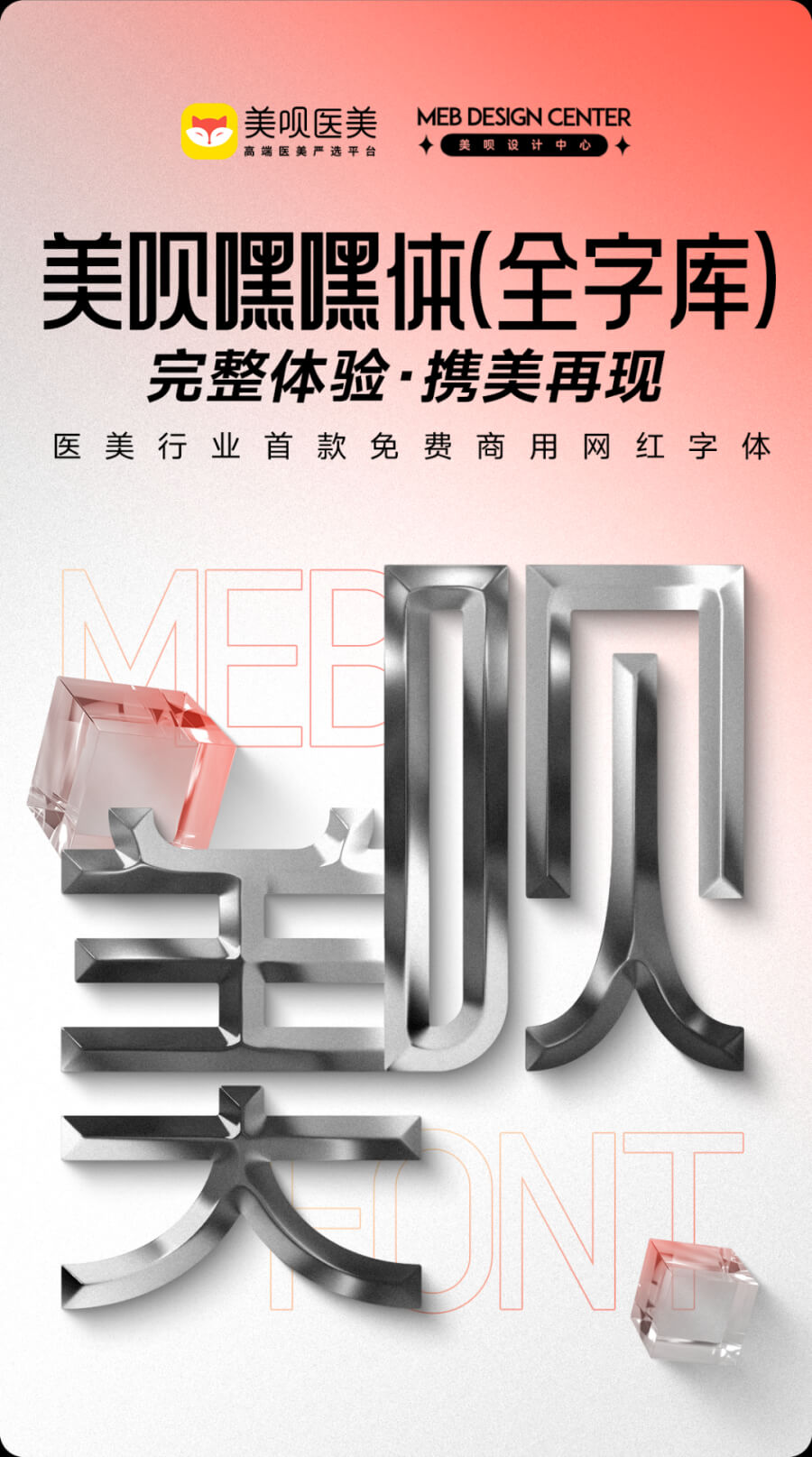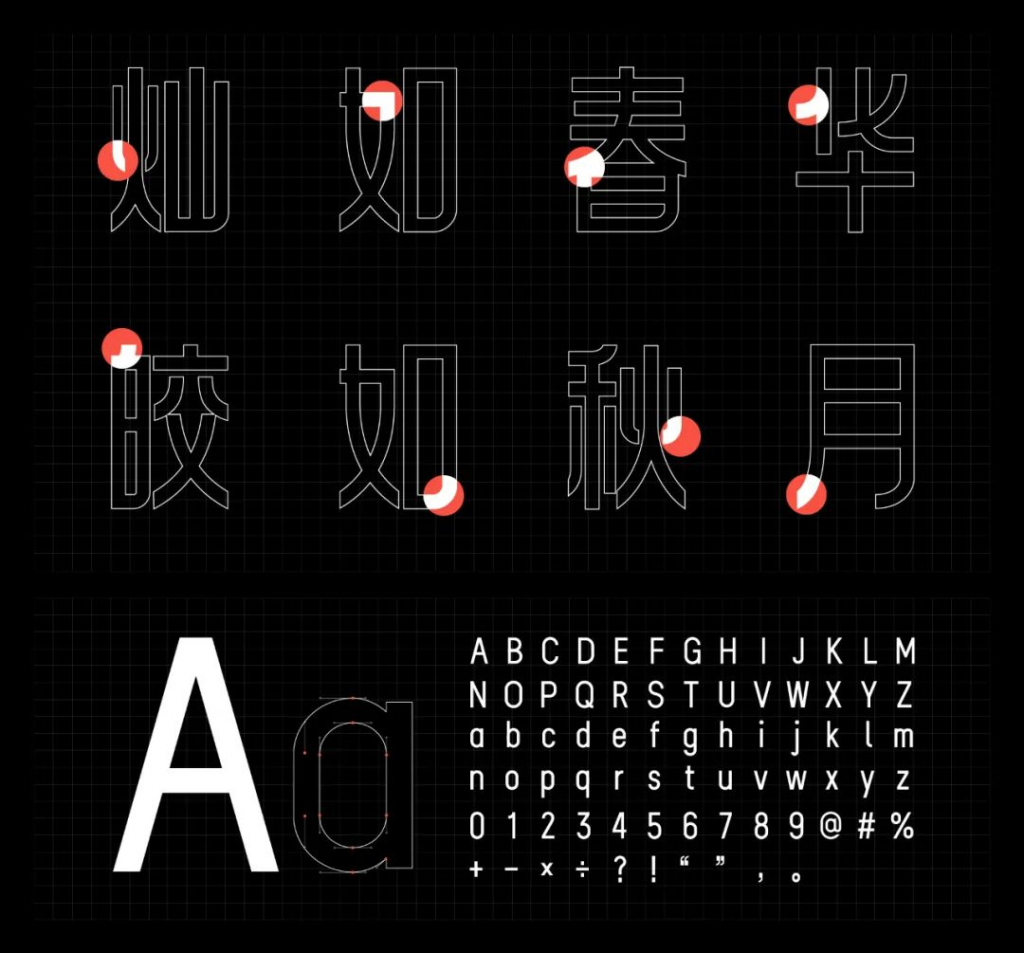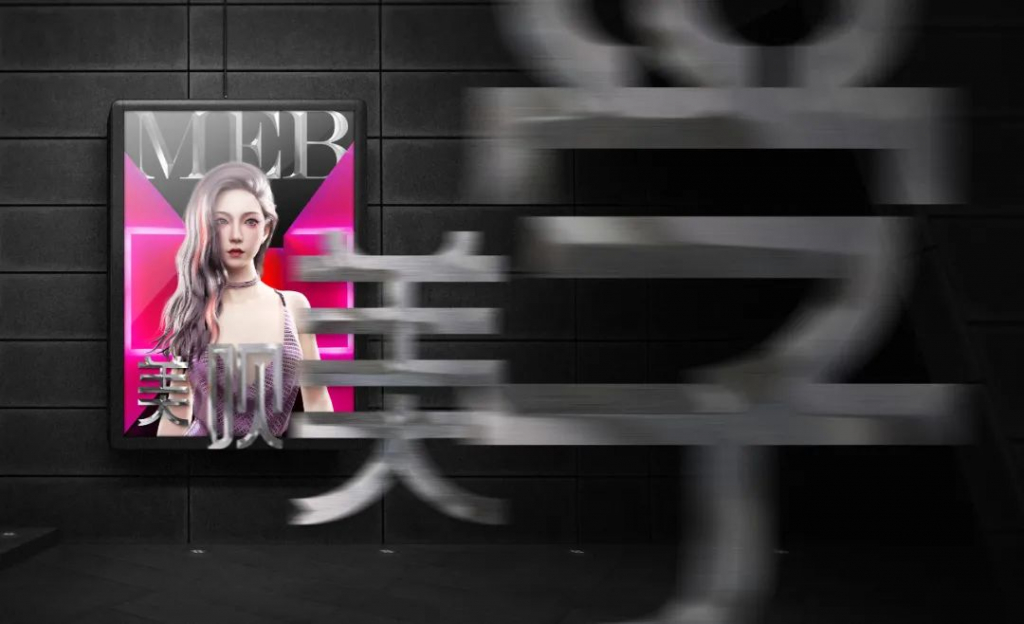
2021年11月1日,由美呗设计中心出品的首款免费商用字体【美呗嘿嘿体】试用版上线,包含2500+个汉字。
2022年末正式推出【美呗嘿嘿体】完整版啦!
●○美呗嘿嘿体,是由美呗设计中心主导设计的一款品牌字体,也是医美行业首款字体。之所以取名美呗嘿嘿体,一是因为这款字体本身属于黑体,二是融入了美呗人“乐观、皮实”的精神,故取名“美呗嘿嘿体”。
咳咳,美呗设计团队为了让品牌符号更加鲜明、让美呗er更有归属感,他们秉承着“开放、合作、创新“公司价值观,就这样开启了一项完全0经验的设计字体的工作!
●○秉承公司文化价值观,设计团队在工作之余从构思到完成,整整花了两年半的时间,精心打磨出了一套符合现代美业的商用字体。
●○在过往的一年中,我们总能在各个地方“邂逅”美呗嘿嘿体,品宣海报、线下广告、活动运营页面…这一切都离不开成千上万设计师朋友和大V的分享。让这款原创字体成为免费商用的网红字体。对此,作为创作者的我们当然是欣喜和自豪的,感谢每一位使用者对美呗嘿嘿体的喜爱和肯定!
●○这一年,我们也没有停滞不前,在大家的反馈和期待声中我们终于完成了美呗嘿嘿体(全字库)的设计!符合GB2312简体中文编码字符标准的品牌字体,包含6767个中文字符和150+西文及数字符号。
“美呗嘿嘿体(全字库)3.0”是一款书写很新颖的字体,字体大方,适合各种设计作品使用!欢迎下载!